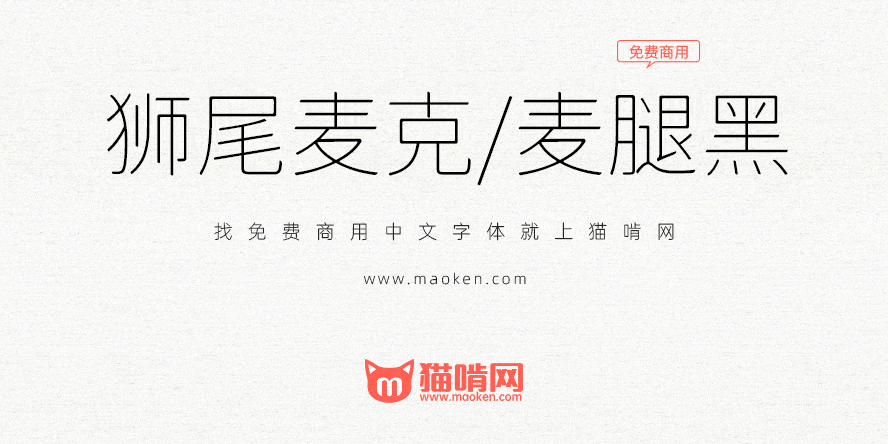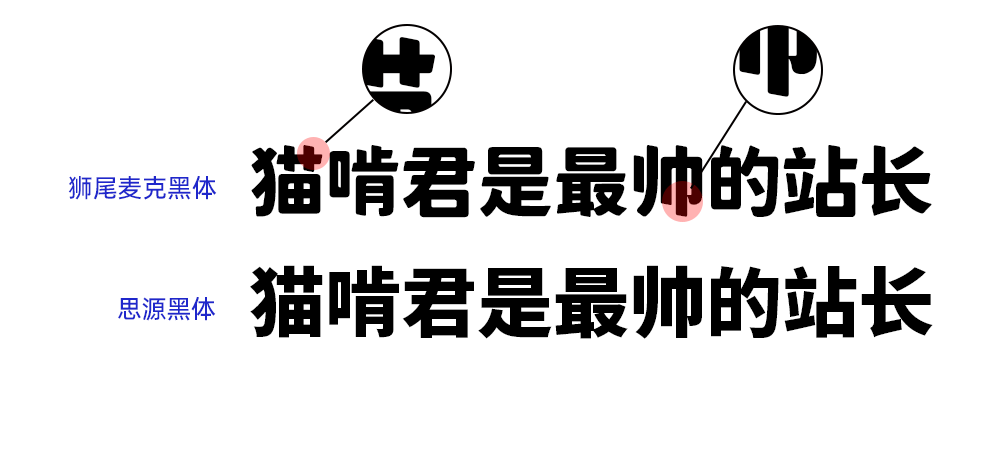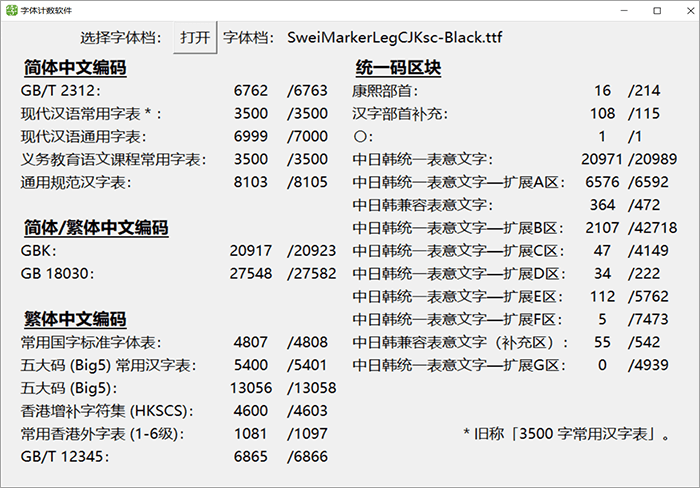
狮尾麦克黑体基于思源黑体的笔触变斜改造,更加简明现代化的字体。狮尾麦克黑体的特色是:笔触略圆,起头与收尾是斜线。下面是狮尾麦克黑体与思源思体的对比效果图。
「狮尾麦克黑体」与「狮尾麦腿黑体」差别在有没有拔脚,「拔脚」就是会有较少的笔画,例如移除「口」字的左右下角会多出的短线条。有拔脚的字会较圆,但是会造成有些字因直接去掉腿后左右不平衡、左右不对衬的「悬空」问题。改使用「腿」系列字体就不会有这个问题。